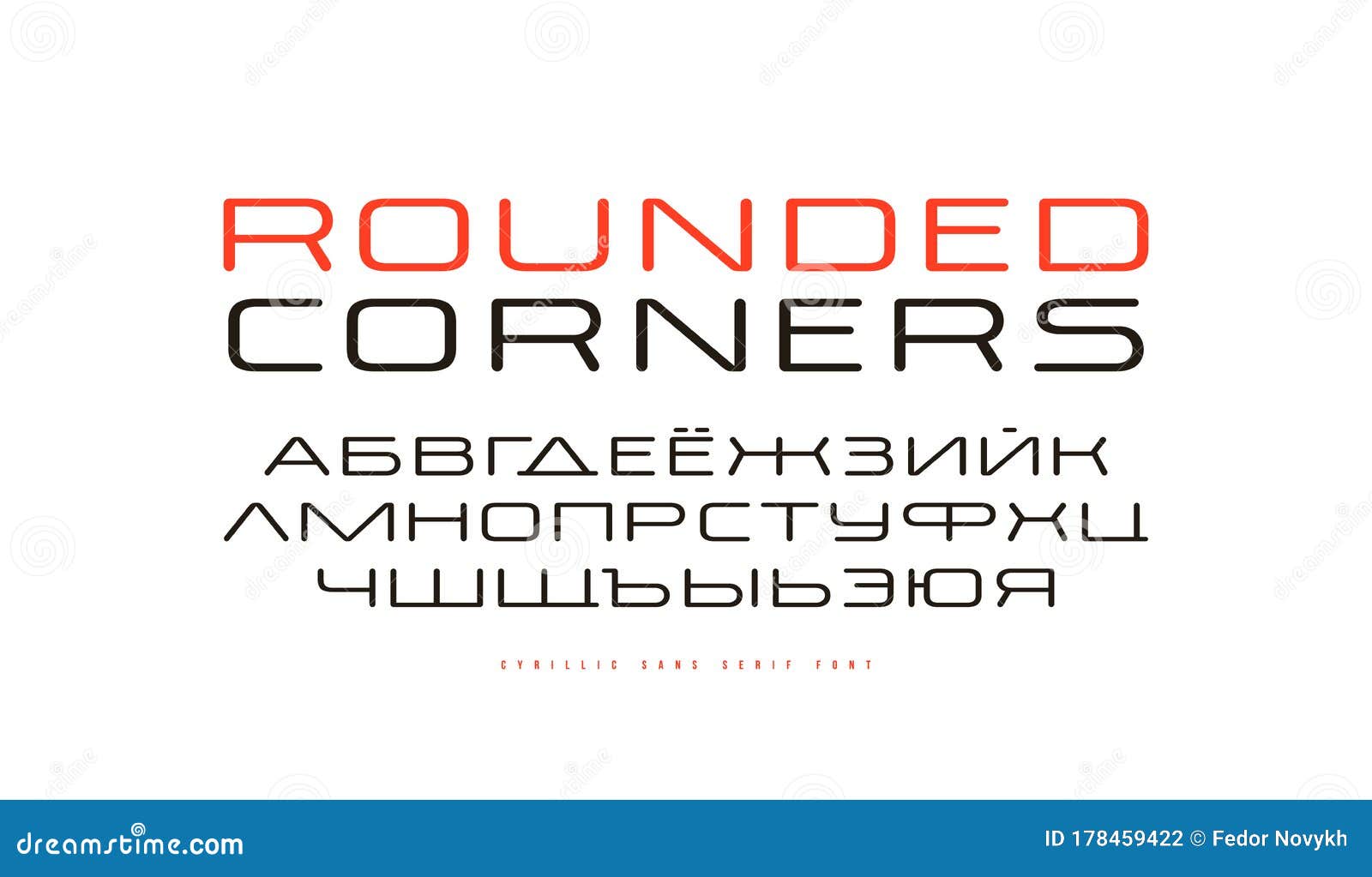
Необычные шрифты кириллицы без засечек - находка для оригинальных дизайнеров и тех, кто ценит изысканность!
Хотите добавить уникальность и элегантность в свои проекты? Рассмотрите наши рекомендации по выбору широкого шрифта кириллицы без засечек, который поможет привлечь внимание и создать эффектную графику. В этом руководстве мы предлагаем лучшие варианты шрифтов и делаем акцент на их преимуществах и использовании.
Выбирайте шрифты с четкими и ясными формами букв, чтобы отображение текста было читабельным и понятным.
Гротеск - шрифт без засечек
Учтите, что не все шрифты без засечек подходят для длинных текстов, поэтому обратите внимание на их читаемость при распечатке и на экране.
Смело экспериментируйте с разными стилями и размерами шрифтов, чтобы достичь наиболее эффектного визуального воздействия.